Haupttitel
Typografischer Terminus für die Seite drei (# 3 Recto) eines Buches oder einer buchähnlichen Publikation (z.B. Geschäftsbericht) mit den bibliografischen Angaben; gelegentlich wird der Haupttitel auch als Innentitel bezeichnet. Der Haupttitel gehört zur Titelei, die dem eigentlichen (Buch)Inhalt vorangestellt wird.
Bereits die Prototypografen widmeten dem Haupttitel eines Werkes besondere Aufmerksamkeit, um dem hohen handwerklichen Status Quo der Kalligraphie ansatzweise gerecht werden zu können. So wurden beispielsweise die Haupttitel in Inkunabeln auch von Illuminatoren und Rubrikatoren kunstvoll gestaltet und verziert.
Traditionell hebt sich seitdem der Haupttitel bis heute mehr oder weniger deutlich in seiner grafischen und/bzw. typografischen Gestaltung von den übrigen Titeleiseiten und den Seiten mit dem eigentlichen Inhalt ab.
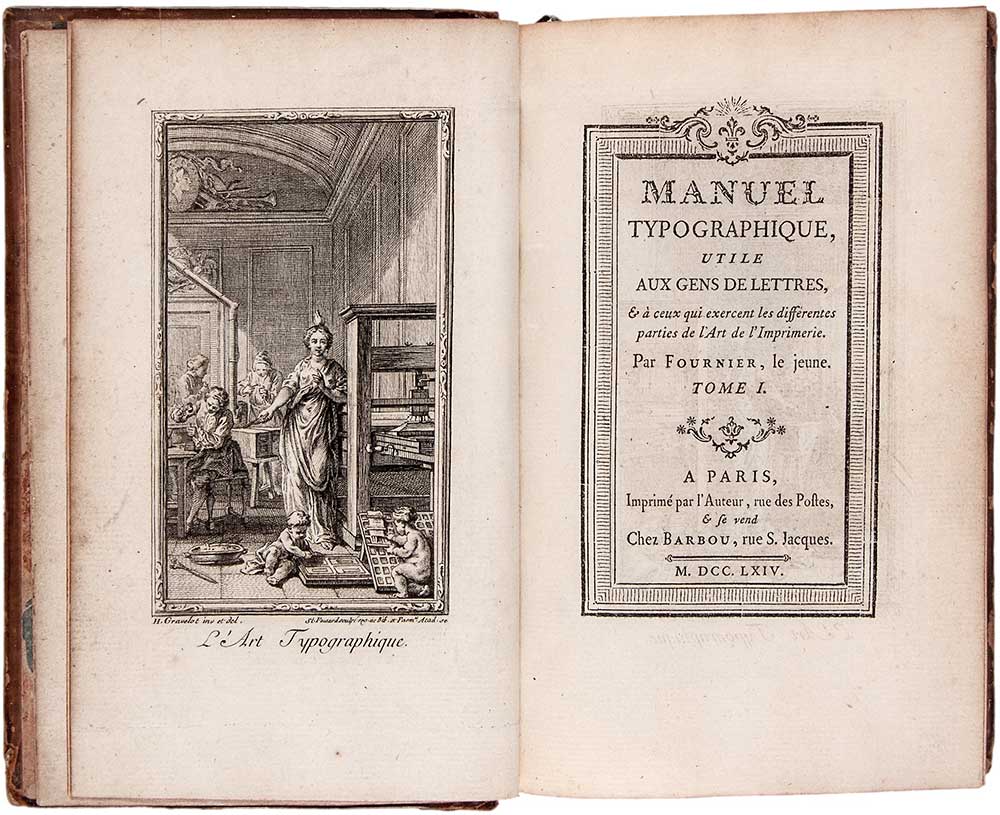
Der deutsche Buchtypograf Albert Kapr (1918–1995) sinnierte über den Haupttitel eines Buches: 1)
»Der Haupttitel hat die repräsentative Funktion des Tores zum Text. Gleichzeitig muss er eindeutige bibliographische Angaben vermitteln (…) Der Haupttitel bietet dem Typografen mehr als jeder andere Teil des Buches Gelegenheit, seine Phantasie und Gestaltungskraft zu zeigen (…) Die Titelseite verdient besondere Sorgfalt, sie steht für die Qualität des ganzen Buches.«
Inhalt
In der Buchgestaltung enthält ein Haupttitel 2) die wesentlichen bibliografischen Angaben eines Buches, die dann auch für die Titelaufnahme in bibliothekarischen und buchhändlerischen Katalogen verbindlich sind. 3) Nachfolgende Inhalte und Gestaltungselemente sind in unterschiedlichen Kombinationen möglich (A–Z):
- Erscheinungsjahr (bzw. Geschäftsjahr) 4)
- Herausgeber
- Illustration (z.B. Alinea oder Einfassung)
- Reihentitel
- Titel des Buches (bzw. buchähnlichen Publikation)
- Untertitel
- Verlag (bzw. Unternehmen)
- Verlagsort (bzw. Unternehmenssitz) 5)
- Vorname, Familienname und ggf. akademischer Titel des Übersetzers
- Vorname, Familienname und ggf. akademischer Titel des Verfassers
Gestaltung
Ein Haupttitel wird in der Regel innerhalb eines Buchsatzspiegels bzw. Gestaltungsrasters und wenn möglich registerhaltig gesetzt. Er kann klassisch oder modern, im Axialsatz oder im anaxialen Flattersatz, mit und ohne Schriftmischungen, in gemischter Schreibweise oder Majuskelsatz bzw. Kapitälchen, mit oder ohne illustrativen Elementen und in unterschiedlichen Schriftgraden gestaltet werden. Die Möglichkeiten sind hier nahezu unbegrenzt. Allerdings sollte der Haupttitel immer auf die Dramaturgie der Titelei abgestimmt werden.
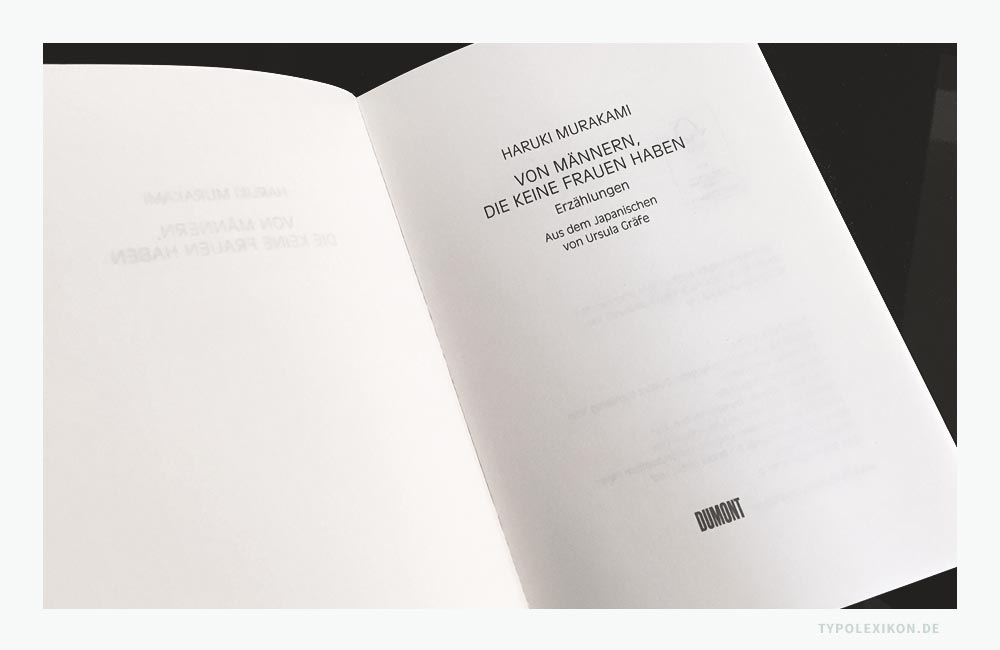
Da der Haupttitel eine besondere repräsentative Aufgabe hat, beziehen ambitionierte Buchgestalter:innen die Seite des Frontispiz in die Gestaltung des Haupttitels mit ein bzw. stimmen diese beiden Titeleiseiten minutiös aufeinander ab.
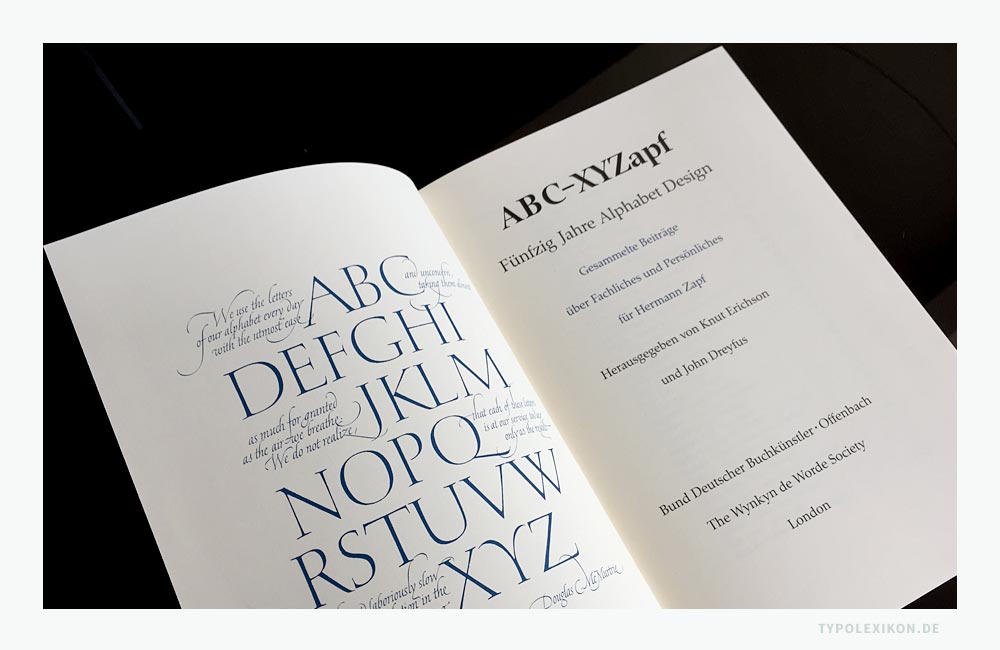
Paginierung
In der Buchtypografie ist ein Haupttitel immer die dritte (rechte) Innenseite, also die dritte Seite (# 3 Recto) eines Buches bzw. einer buchähnlichen Publikation. Der Haupttitel befindet sich zwischen dem Frontispiz und dem Impressum, das dem Haupttitel auf der Rückseite (# 4 Verso) folgt.
Der Haupttitel ist zwar rechnerisch die Seite # 3 eines Buches, wird aber nicht mit einer Pagina (Seitenzahl) bzw. einem Kolumnentitel versehen, da diese eine Titeleiseite ist und die eigentliche Paginierung erst mit dem Inhalt erfolgt
Der Haupttitel befindet sich bei gewerblichen Hauptdruckverfahren auf dem ersten Druckbogen (Rohbogen) oder einem separaten Titelbogen (siehe Titelei). 6)
| ↑1 | Quelle und Literaturempfehlung: Kapr, Albert: Hundertundein Sätze zur Buchgestaltung, Deutsche Bücherei Leipzig, 1974, aus den Lehrsätzen 59, 60 und 63 auf Seite 27 und 28. |
| ↑2 | Anmerkung: Für »Haupttitel« wird – sehr selten – auch das Synonym »Innentitel« verwendet, beispielsweise von Hans Peter Willberg. Quelle und Literaturempfehlung: Willberg, Hans Peter und Friedrich Forssman: Lesetypografie, Verlag Hermann Schmidt, Mainz, ISBN 978-3-87439-800-8, Seite 316. |
| ↑3 | Anmerkung: Der Buchtitel und der Haupttitel eines Buches sind unterschiedliche Bezeichnungen. Der Buchtitel ist wortwörtlich zu nehmen, der Haupttitel eines Buches ist jedoch wie oben beschrieben die Titeleiseite 3 (# 3 Recto). |
| ↑4 | Anmerkung: Verlagsort und Erscheinungsjahr können auch auf der Rückseite im Impressum stehen bzw. bei Unternehmenspublikationen – außer bei Geschäftsberichten – auf den Seiten nach dem Inhalt. |
| ↑5 | Anmerkung: Verlagsort und Erscheinungsjahr können auch auf der Rückseite im Impressum stehen bzw. bei Unternehmenspublikationen – außer bei Geschäftsberichten – auf den Seiten nach dem Inhalt. |